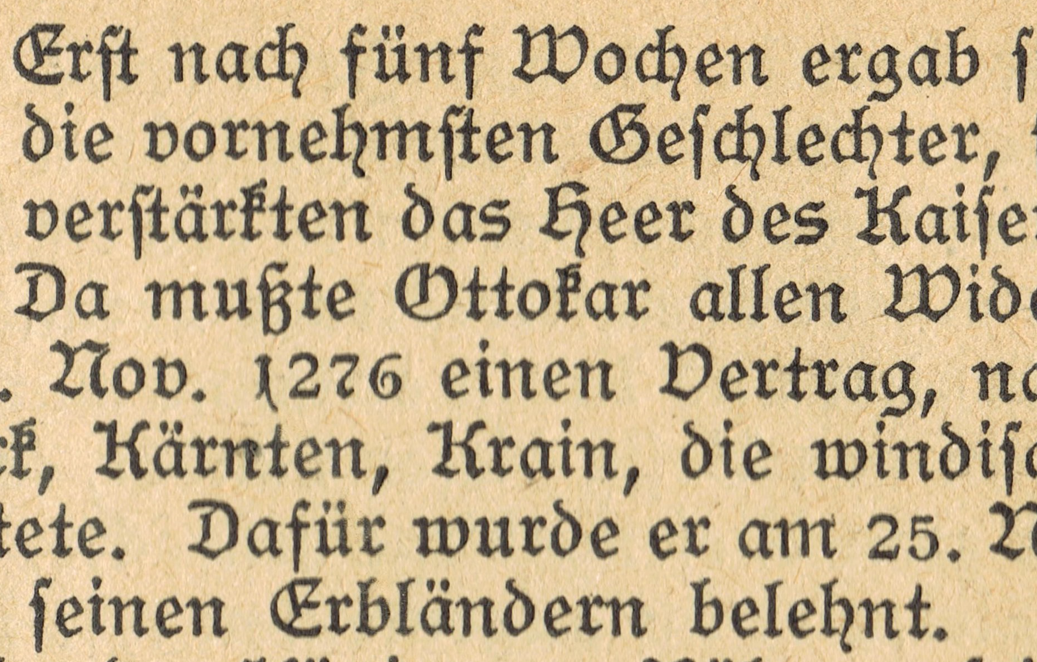
Mit welcher Schwabacher habe ich es hier zu tun, und...
wie komme ich an die Glyphen q,  Q, X  und Y?
Ich bin durch die Anfrage wegen der Zeugkiste-Schrift auf die Idee gekommen, basierend auf meiner Schreibmaschinen-Schrift mit Pseudo-Zufall Glyphenrotation dieses OpenType-Script für eine gebrochene Schrift auszuweiten.
Ich habe da ein kleines Taschenbuch "König Ottokars Glück und Ende von Grillparzer, als billigste Schulausgabe  mit entsprechend nicht gerade perfektem Druck in einer Schwabacher, wie sie von vielen Schriftgießereigen mehr oder weniger austauschbar angeboten wurde. Zu 100% ist sie aber leider nicht identisch mit den Abbildungen im Seemann S. 22-24, aber selbst wenn das etwas Zwiebelfischig werden sollte, stört mich das kaum, und auch wenn ich da keine 10 leicht verschiedene Abbildungen zusammen bekomme, braiucht man diese Lettern doch wirklich sehr selten.
Auch denke ich, für diesen Zweck keine idealisierte Digitalisierung zu planen, sondern aus den Autotrace-Scans bewusst Glyphen mit Macken heraus zu wählen. Meine OpenType-Logik muss ich ja schon um zumindest dem langen s und den sehr oft verwendeten Ligaturen  ch und ck ergänzen, andere Ligaturen habe ich jedoch nicht gefunden.
Es wäre sehr schön, könnte man mir mit den im ganzen Text nicht auffindbaren Buchstaben aushelfen.
Das scheint mir die "Neue Schwabacher" oder auch nur "Schwabacher" zu sein.